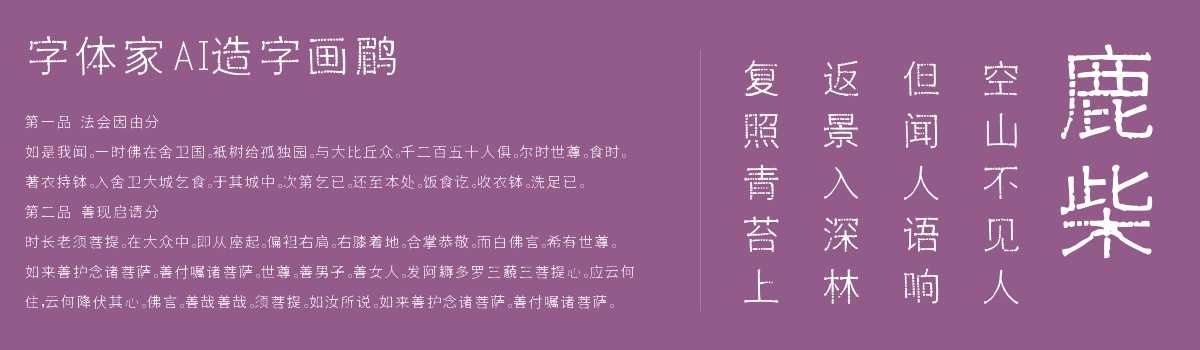
字体家AI造字画鹛
字体家AI造字画鹛是一款由字体家AI神笔造字生成的艺术字体,这是一款无衬线字体,笔画粗细均匀,横纵笔画宽度接近,无明显粗细对比。结构方正,间架匀称,重心平稳如磐石。转折处呈利落方角,边缘平滑似打磨过的玉石,无毛刺。起笔收笔干净,像用尺子划出的直线般规整,无多余装饰。整体端庄稳重,像端坐的君子,简洁中透着力量,易读性强,摸上去应是平滑温润的触感,现代感与质朴美交融。适合用于一些广告标题、平面文案、海报标题、网页广告用字的编辑。